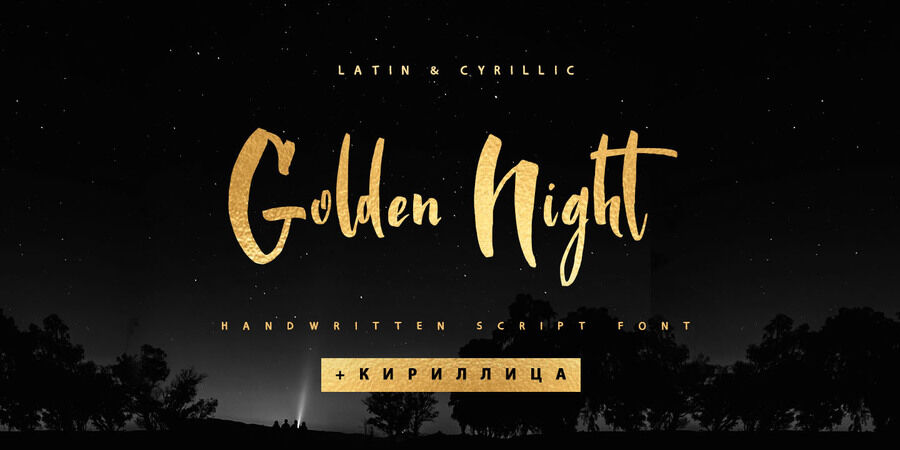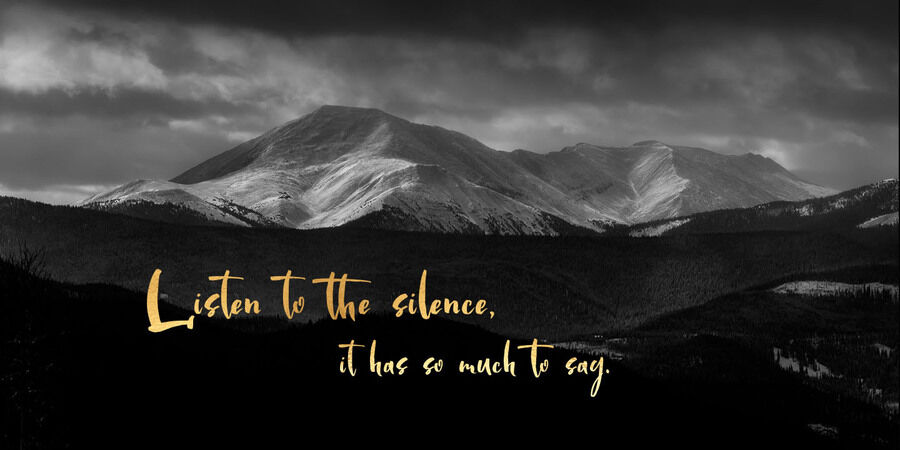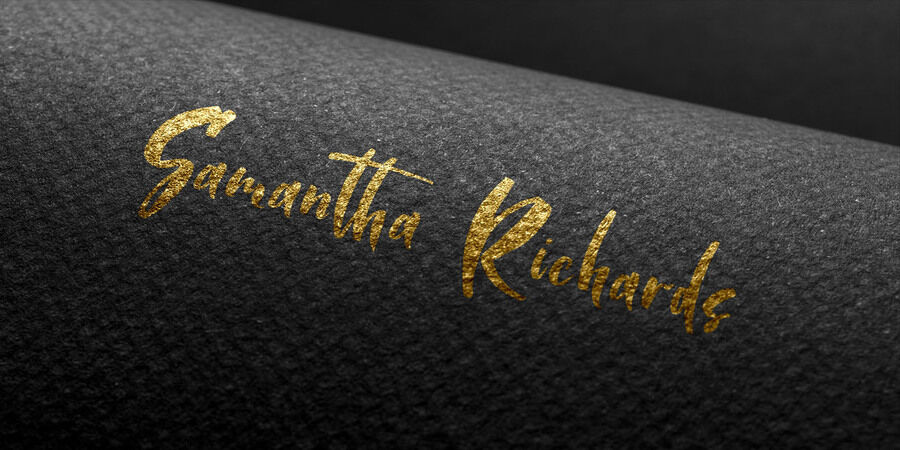
Рукописний шрифт з підтримкою кирилиці, який ідеально підходить для брендингу, логотипів, соціальних мереж, етикеток, дизайну упаковки і заголовків блогів. Шрифт Golden Night містить повний набір великих і рядкових літер, 32 лігатури в латиниці а також 18 лігатур в кирилиці які включені автоматично для створення більш природного рукописного виду. Включена мовна підтримка для 31 мови. Кирилиця підтримує російську, українську, білоруську та болгарську мови. Шрифт розробила Ірина Двілюк у 2021 році.
Особливості сімейства шрифтів Golden Night CyrillicХіт десятиліття:
Асоціації з сімейством шрифтів Golden Night CyrillicОсобистість і характер гарнітури:
швидкий, артистичний, органічний, динамічний, свіжий, неохайний, веселий, легковажний, емоційний, рідкий, лихий, рухливий, непосидючий, мультяшний, яскравий, смачний, смішний, добрий, милий, М'який, ремісничий, рукотворний, ручний, доброзичливий, довірчий, зелений, натуральний, природний, грайливий, потішний, прикольний, живий, оригінальний, привітний, характерний, святковий, соковитий, стиглий, крафтовий, радісний, пустотливий, весняний, літній, щасливий, нервовий, стрибучий, танцюючий, моторний, вернакулярний, вільний, розмашистий, модний, сміливий, цікавий, енергійний, темпераментний, самобутній, художній, мрійливий, виразний, амбітний, помітний, творчий, експресивний, активний, мотивуючий, романтичний, нічний
весна, кафе, інтер'єр, квіти, подарунки, хенд мейд, їжа, відпочинок, природа, анімація, мультфільм, торгівля, розваги, піцца, живопис, фарби, кава, Інстаграм, косметика, краса, мода, одяг, закуска, танець, музика, ресторан, свято, Новий рік, золото, виставка, селфі, романтика, графіка, ілюстрація, захід сонця, вечір, пейзаж, акварель Гарнітура має ознаки стилів: